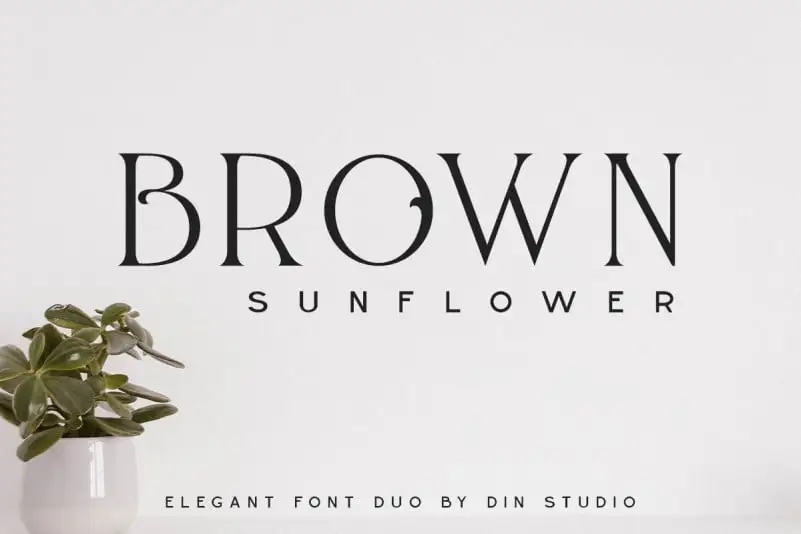
Brown Sunflower Display Font – Fonte Grátis
Brown Sunflower Display Font
A fonte Brown Sunflower Display é uma elegante e sofisticada serif que se destaca na categoria das tipografias display. Com seu mix de modernidade e nostalágica, esta fonte é perfeita tanto para logos quanto para revistas e redes sociais. Suas linhas leves e serif decorativa permitem que você ressalte o texto sem a necessidade de recurso barato ou simplista. Brown Sunflower oferece um toque moderno ao mesmo tempo em que torna seu design ainda mais belo e sofisticado, uma combinação única entre as linhas leves do serif clássico e a estética minimalista do sans-serif decorativo. Engane-se para não notar o poder de impacto dessa fonte. Eles são a escolha perfeita para designers que desejam criar elementos visuais imprimíveis com estilo e sofisticação, seja para uma marca digital ou um projeto de revista impressa.